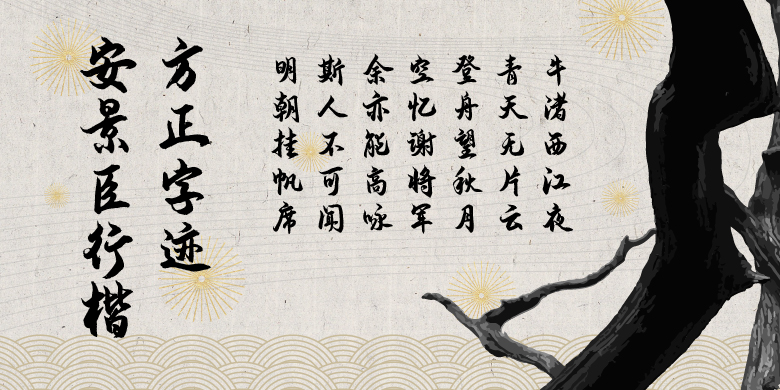
方正字迹-安景臣行楷
方正字迹-安景臣行楷,这款字体结构工整、笔画清晰,兼顾美观与易读性,适用于标题、正文、海报、包装、LOGO 等多种场景。字形优雅稳定,风格百搭耐看,适配日常排版与创意设计,让文字呈现更舒适、更具质感。方正字迹-安景臣行楷一笔一画,皆是细节,以均衡的比例、流畅的线条打造舒适视觉体验,字形端正大气,风格简约现代。无论是商业设计、品牌宣传还是日常排版,都能轻松驾驭,让文字更有格调与力量。方正字迹-安景臣行楷字体下载。
字体品牌: 方正字迹 设计师:安景臣 字体分类:行楷、行书 字体属性:精品字 字符集:大陆简体(GB2312-80)、简繁扩展(GBK) 发布时间: 2021
安景臣行楷既有传统书法功底,又有鲜明的时代特色与个性风格。此款字体在吸收传统书法风格,诸如王羲之、米芾、赵孟頫等书法字体风格的基础上,加上借鉴现代任政行书等的特点,比传统书法更具规范性,同时比现有电脑行楷体灵活生动、更具文化气息与实用性,适用于传媒公司、大型企业、商家店铺广告标题等及排版印刷正文采用。
安景臣,1972年生,自幼酷爱书画艺术,数十年来笔耕不辍,对历代名帖心摹手追、转益多师,渐有收获。书法作品多次获奖。并爱好诗歌、歌词创作、音乐、篆刻等。入围第四届“方正奖”字体设计大赛,有多款电脑字体被大型集团选为广告语专用字体,并上线手机主题商店等。